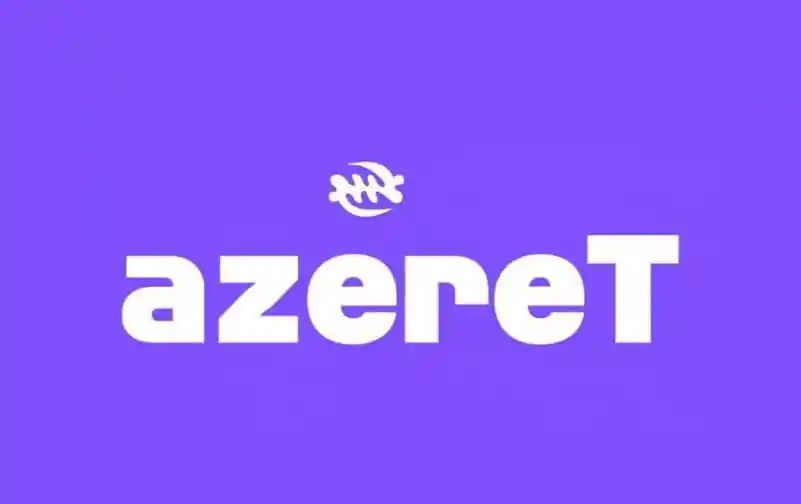
Azeret Sans Serif é uma elegante fonte de linhas retas que surgiu através de um processo de investigação atemporal e futurista. Suas origens remontam a um esboço inspirado no uso da OCR (Optical Character Recognition) para sistemas operacionais passados e futuros, interfaces digitais diversas e o cenário dos anos 90. Após essa pesquisa meticulosa, a fonte convergiu em uma aparência que transmite leveza e modernidade. O design de Azeret busca uma elegância minimalista mas também consegue capturar os detalhes que criam um tom único. É perfeita para aplicações digitais, como sites, aplicativos ou editoriais online onde se deseja um look contemporâneo e eficiente. Esse é o tipo de fonte com a qual você pode criar uma experiência digital fluida e atraente.